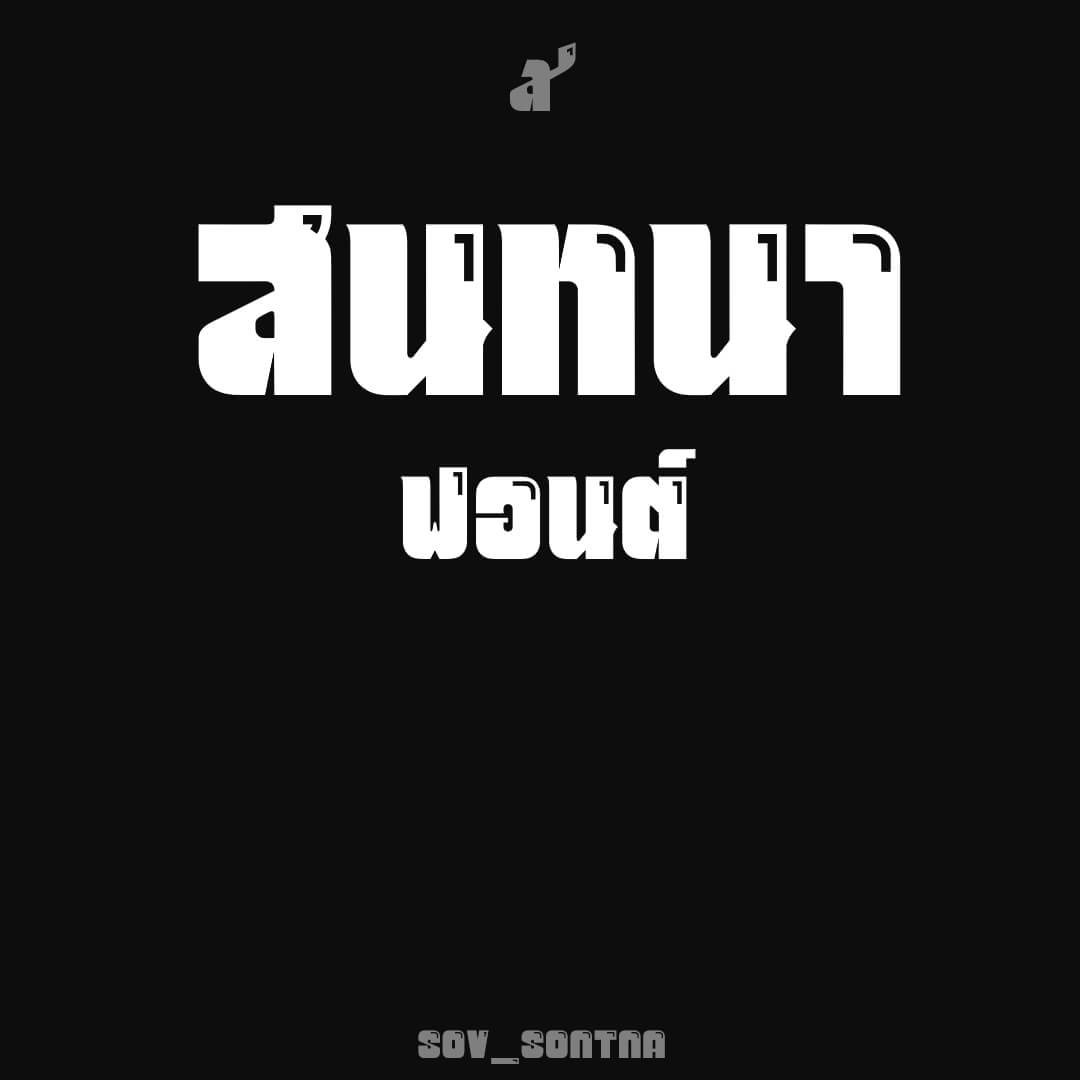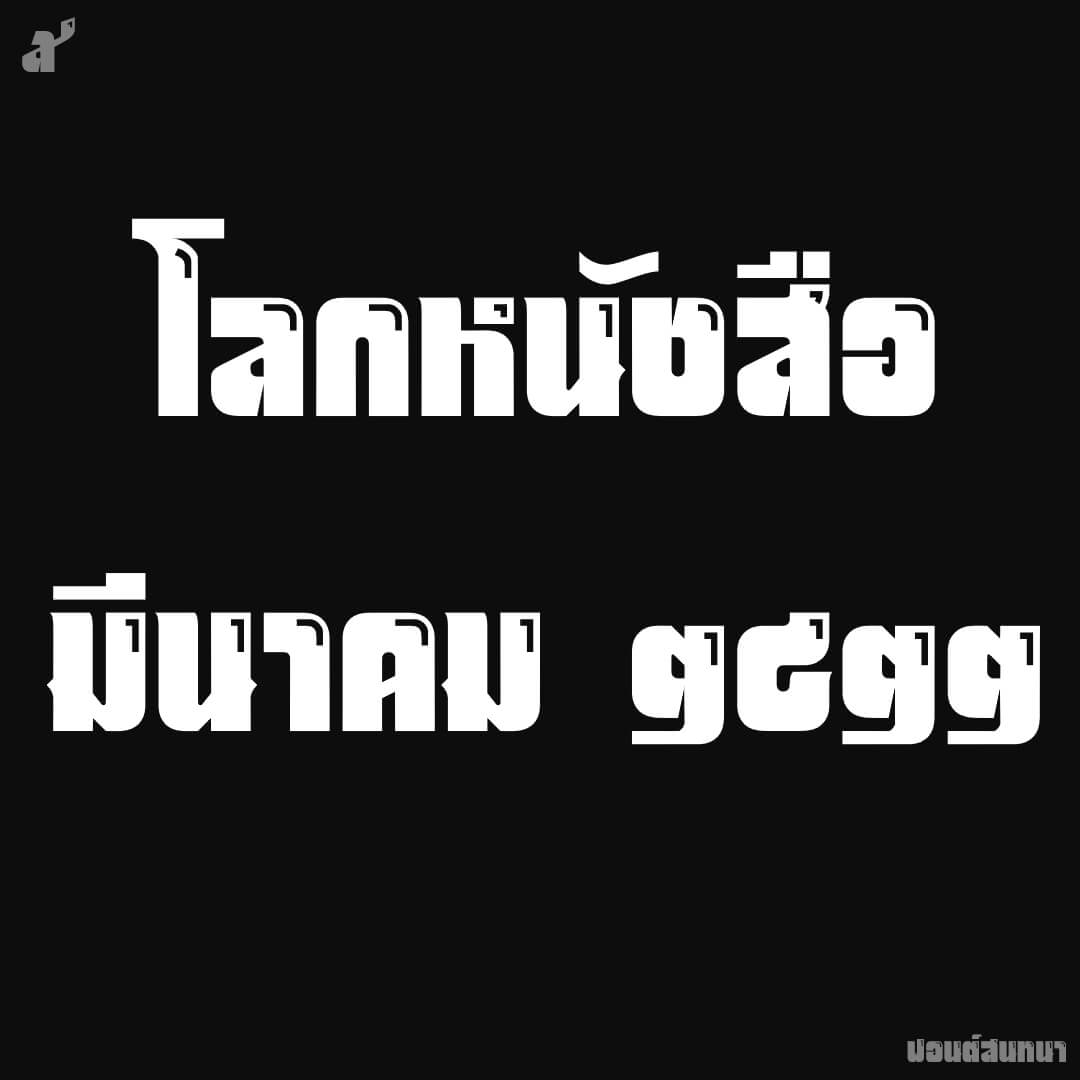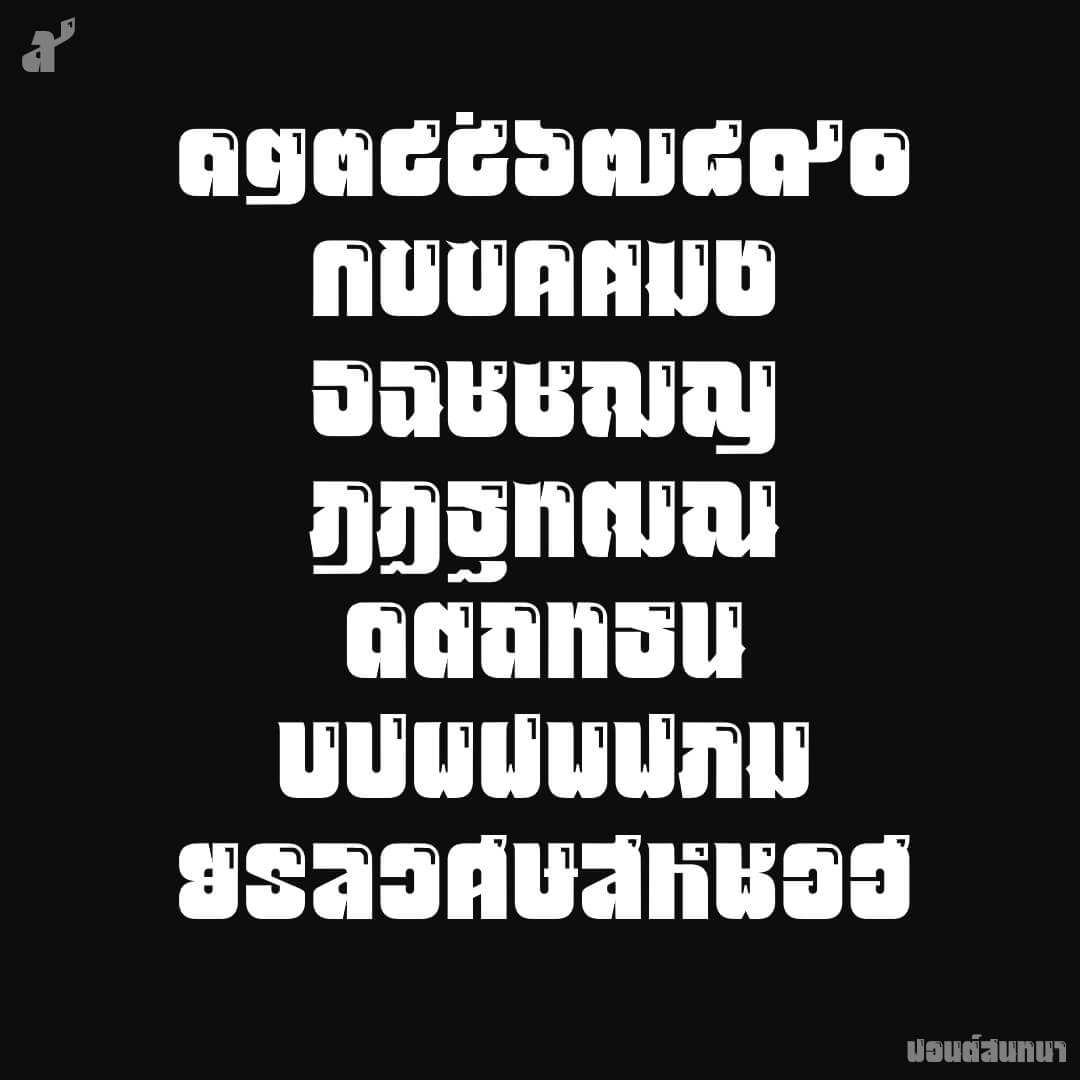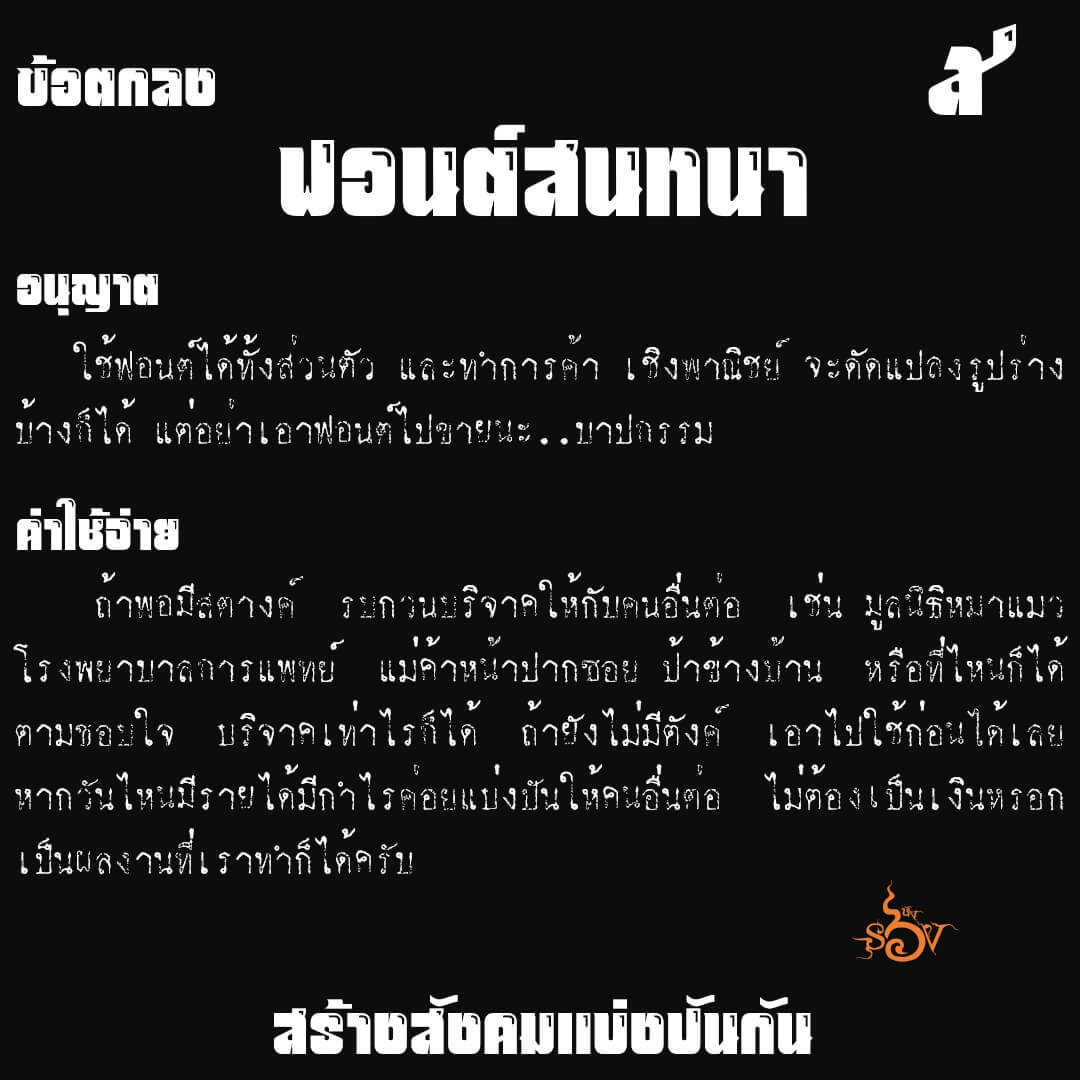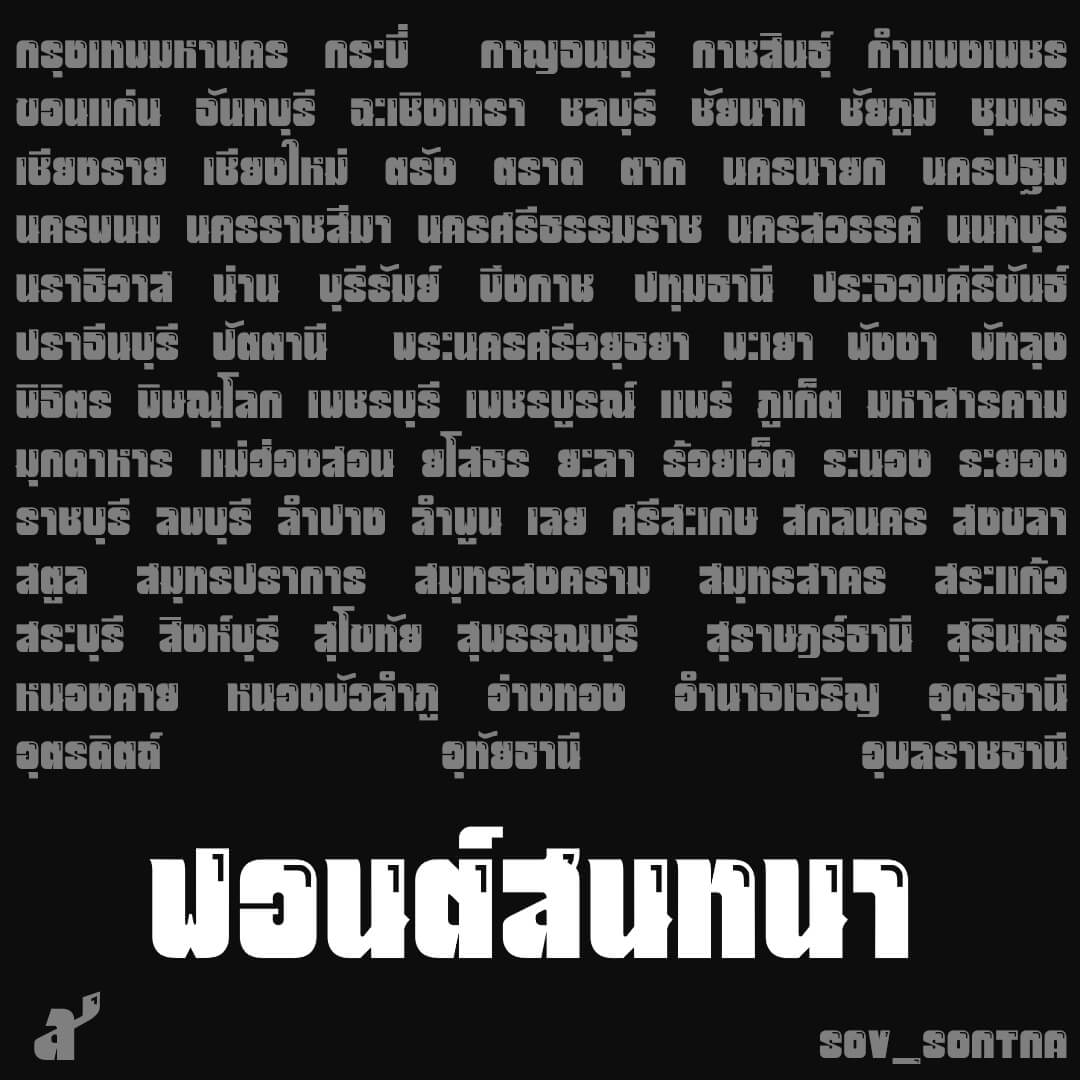
ฟอนต์สนทนา – ต้นทางจากโลกหนังสือ ฉบับ มีนาคม ๒๕๒๒ อักษรไม่มีหัวเมื่อเกือบ 50 ปีที่แล้ว ฟอนต์ดูแข็งแรงแม้จะมีมุมโค้ง… เลยแอบเติมจุดตรงมุมให้ดูป่องขึ้น
เบื้องหลังการออกแบบ : ฟอนต์ สนทนา
สนทนา (SOV_Sontna)